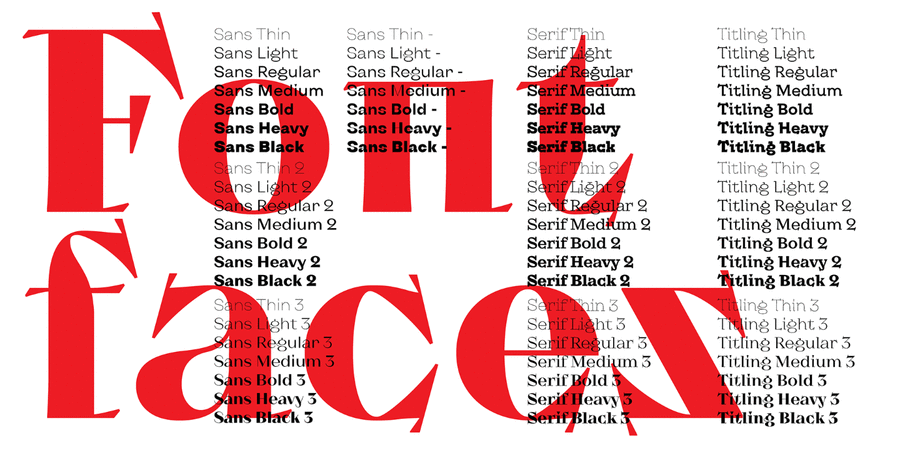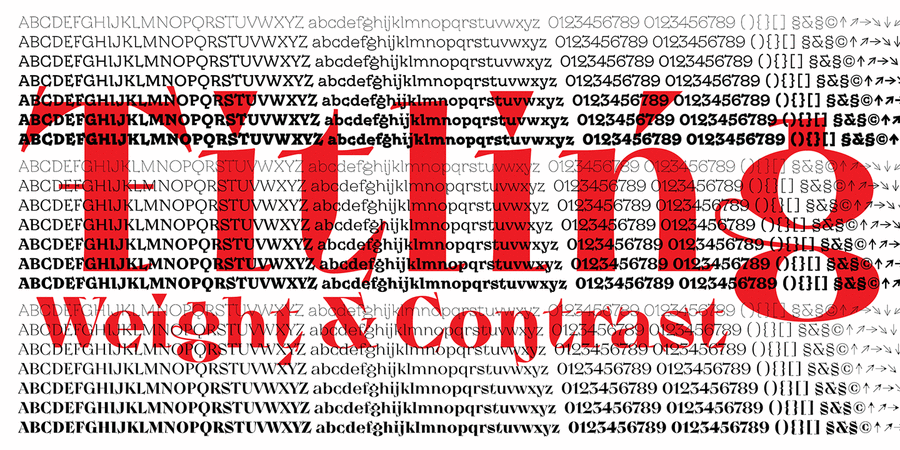
Акцидентна частина супергарнітури для Києва. Шрифт для Києва з багатьма обличчями та крутим характером з'явився тоді, коли до проекту #newkyivlogo (каштановий лист як логотип Києва) приєднався Дмитро Растворцев. «Київ різний. Трохи брутальний. Трохи інтелігентний. Трохи тусовочний. Трохи хіпстерський. Трохи традиційний. Це еклектичне місто. Воно легко включає різне та різних – це створює той Київ, який я люблю. Шрифт такий самий – трохи брутальний, трохи інтелігентний, трохи тусовочний, трохи традиційний, трохи дикий. І дуже-дуже різний.» – так описує проект Олександр Трегуб – засновник Projector та ідейний натхненник нового логотипу Києва.
Асоціації з сімейством шрифтів Kyiv Type TitlingОсобистість і характер гарнітури:
гострий, сміливий, самобутній, характерний, оригінальний, вільний, різкий, етнічний, традиційний, старовинний, козацький, вольний, гордий, дотепний, колоритний, артистичний, художній, благородний, консервативний, пафосний, вишуканий, майстерний, аристократичний, якісний, історичний, гуманітарний, динамічний, осінній, казковий, красивий, виразний, прекрасний, ритмічний, твердий, чіткий, добротний, ностальгічний, ремісничий, рукотворний, золотий, ювелірний, дорогий, розкішний, дзвінкий, елітний, культурний, старомодний, сексуальний